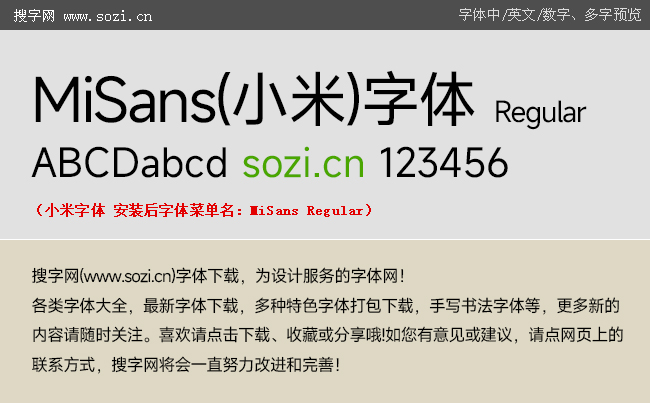
MiSans(小米)字體-Regular
搜字網(wǎng)給大家提供一款MiSans(小米)字體-Regular中文字體下載,MiSans(小米)字體是隨著 MIUI 13 的更新,帶來(lái)的全新系統(tǒng)字體,這款中文字體顯示效果清晰銳利,設(shè)計(jì)簡(jiǎn)約優(yōu)雅,小米還讓此字體供全社會(huì)免費(fèi)商用!
• 風(fēng)格類(lèi)別: 黑體